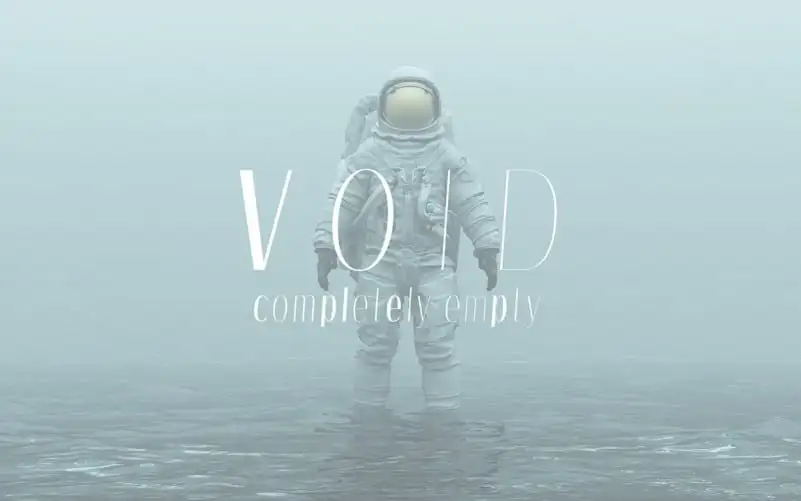
VOID Sans Serif Font – Fonte Grátis
VOID Sans Serif Font
A VOID Sans Serif Font é uma escolha moderna para projetos profissionais que valorizam simplicidade e elegância. Especialmente adequada para marcações impressas, logotipos e design de sites, essa fonte também pode ser usada em designs românticos e para tags de letra, como no caso do desenho de tênis de couro. Seu único objetivo é complementar o estilo da sua marca ou projeto, oferecendo uma aparência clara e atraente que se encaixa perfeitamente com qualquer ambiente gráfico. Criada e compartilhada pelo sartstudio, a VOID Sans Serif Font traz aos projetos um toque elegante e único em cada letra. Ela é ideal para aqueles designers buscando uma opção moderna que combine funcionalidade e beleza sem comprometer a sofisticação.